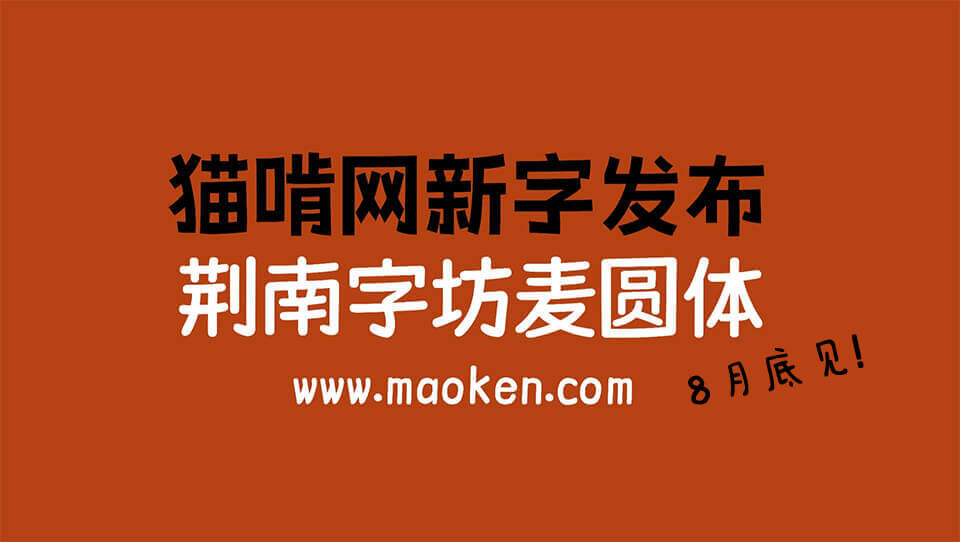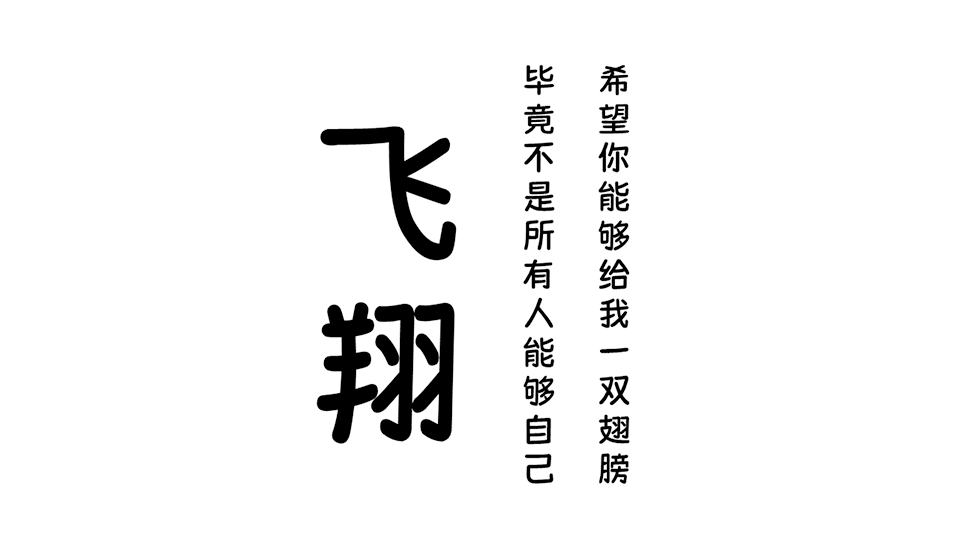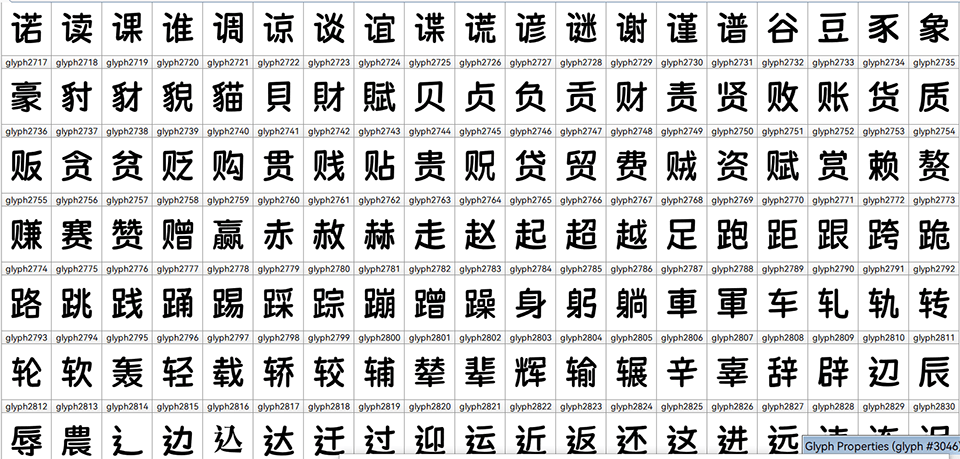
荆南字坊麦圆体即将上线 8月31日约定见你!Comming Soon!
不知道大家用荆南缘默体用得怎么样?用得爽不爽?告诉大家一个好消息,荆南缘默体的作者@荆南字坊准备又有新作啦!!而且老规矩,不要998,不要98,免费商用带回家!对的,你没看错,还是免费商用!猫啃君又来提前剧透啦!
荆南字坊麦圆体的设计灵感来源于韩国的一个综艺节目上的谚文字体,手写的风格圆润的笔画让这款字体看起来很可爱。
麦圆体萌系可爱的手写风格,字体每个笔画的粗细相同,两端圆润饱满,凸显可爱风格。虽是手写字体,笔画分明没有细小的连接,使字体更加清新俏皮。无论是做食品类还是母婴类,抑或是儿童类的设计都特别适合。
据字体作者@荆南字坊介绍,荆南字坊麦圆体计划完全开源,方便大家有兴趣的话可以加入补字的系列。现在麦圆体已经完成GB2312的第一基准的所有字了,准备进行测试和修正,预计八月月底与大家见面。